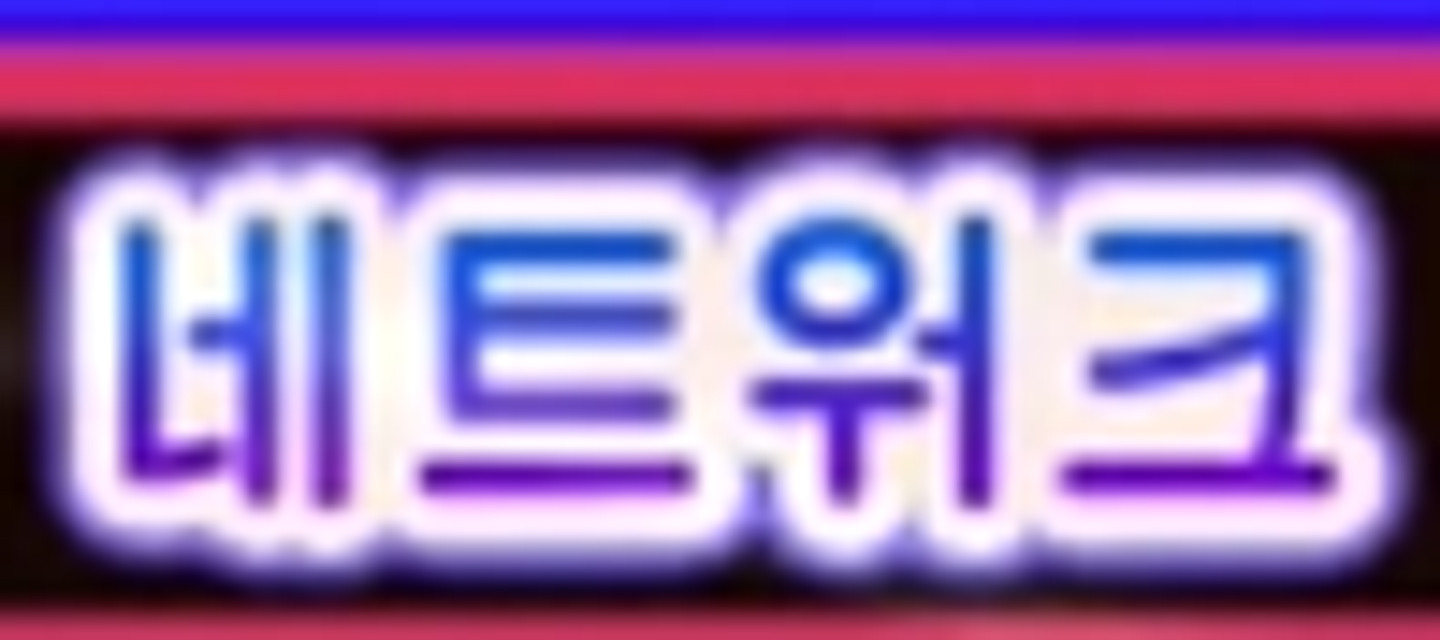
팝픈 뮤직 유니랩에서 사용되는 한글 폰트인 것 같은데 아무리 검색해도 똑같은 폰트가 안 보이네요... 무슨 폰트인지 아시는 분 계실까요?
천리마
북한제 폰트인 천리마체 혹은 본문고직체로 보입니다. 코나미는 팝픈뮤직을 비롯한 수많은 게임에 북한제 폰트를 사용한 적이 있습니다.